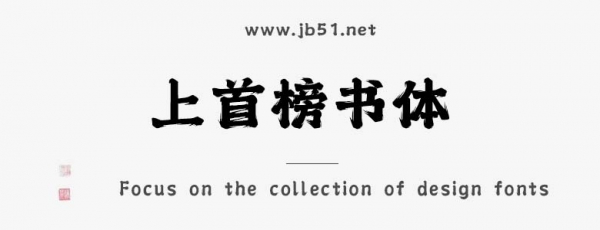
上首榜書(shū)體是由上首造字字庫(kù)出品的字體,字體筆觸略粗,字形端正,具有很好的視覺(jué)感,適合應(yīng)用于藝術(shù)設(shè)計(jì)、平面宣傳設(shè)計(jì)、網(wǎng)頁(yè)設(shè)計(jì),書(shū)法字帖等領(lǐng)域,需要的朋友可以前來(lái)本站下載。